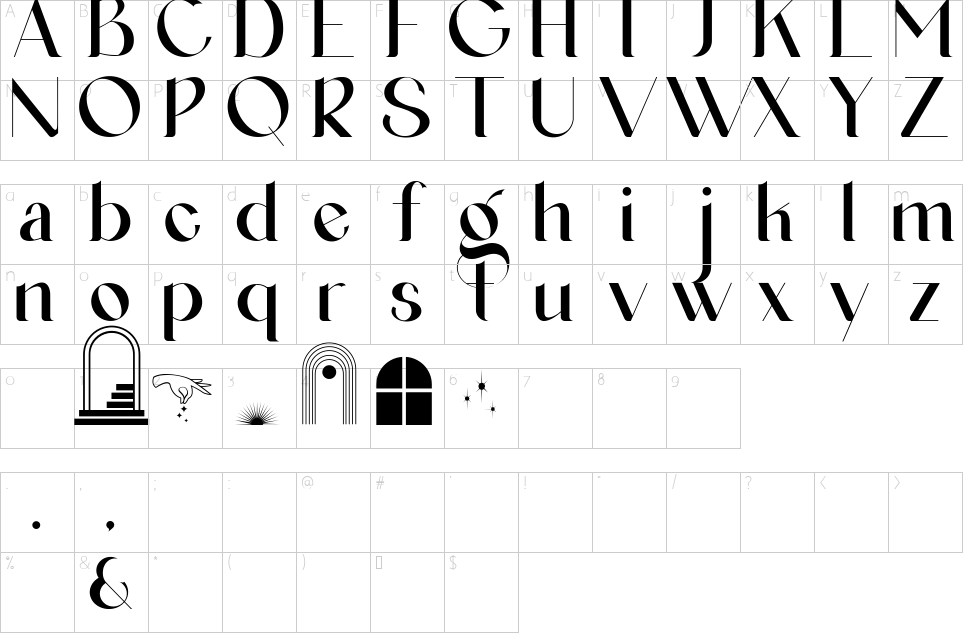
Agraham Font
Agraham é uma fonte que oferece um estilo natural e envolvente, ideal para qualquer projeto gráfico que busca uma sensação natural e aconchegante. Desenvolvida pelo designer putu dody permana, Agraham foi projetada para trazer uma paleta de cores suaves e linhas arredondadas que se adaptam bem a textos em páginas de revistas, sites, ou até mesmo em trabalhos de design gráfico. É especialmente adequada para aplicativos de Windows e Mac, proporcionando uma experiência visual harmoniosa e confortável. Com seu download fácil e gratuito, Agraham não só enriquece seu trabalho com uma fonte de qualidade, como também ajuda a estabelecer uma conexão direta com seus leitores ou usuários. Como fonte oferecida de graça, é uma ótima maneira de incorporar uma escolha de fonte de alta qualidade em seu projeto sem precisar gastar muito.
Mapa de caracteres da fonte Agraham Font